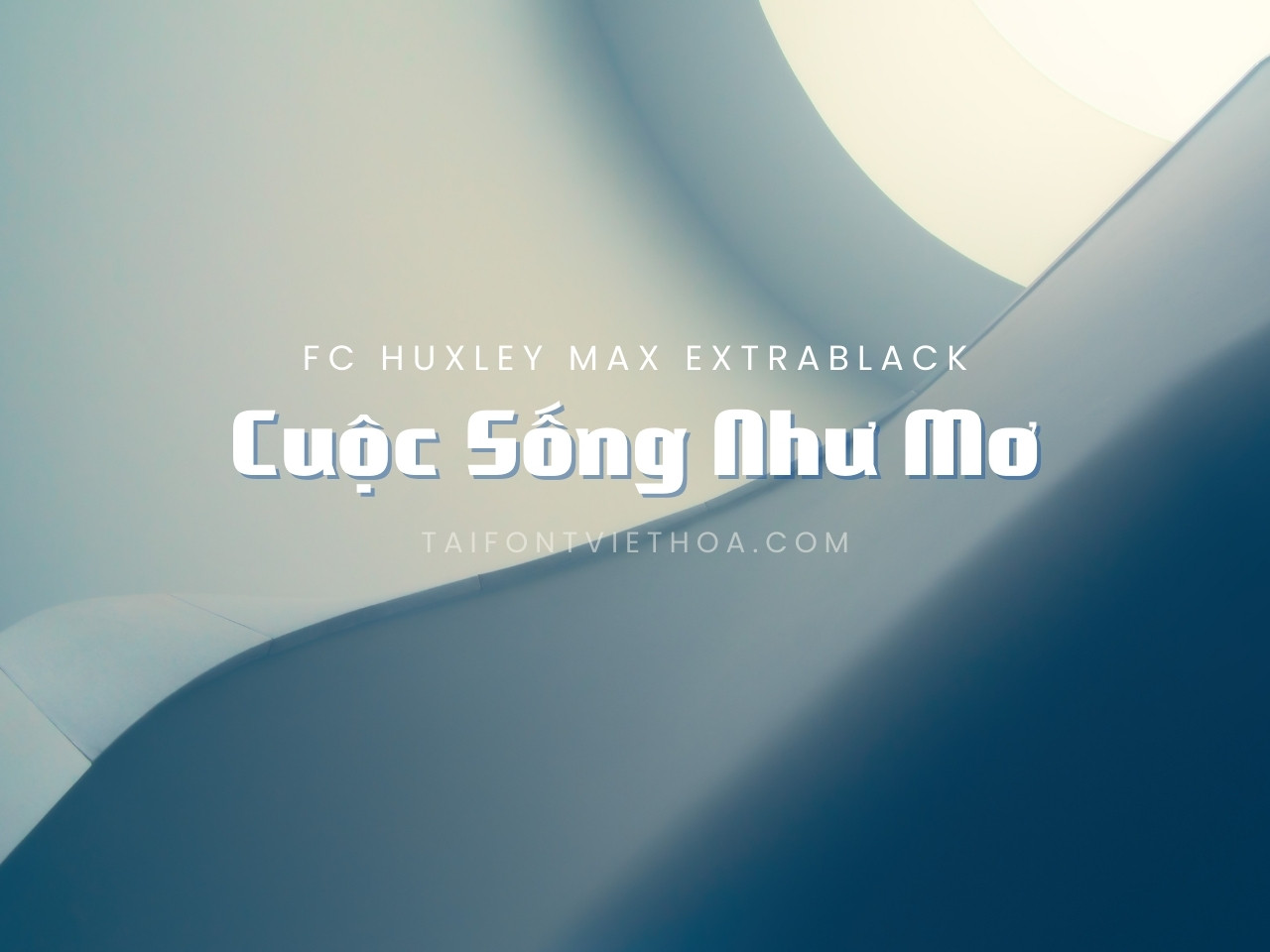
Giới thiệu về font Huxley Max và phiên bản Việt hóa
FC Huxley Max Extrablack là phiên bản Việt hóa từ bộ font “Huxley Max” – một thiết kế sans-serif mang phong cách hiện đại và đầy trọng lượng. Được phát triển bởi hãng thiết kế nổi tiếng Canada Type, font Huxley Max là bản mở rộng của kiểu chữ Huxley Vertical ra mắt từ những năm 1930, nhưng được tái thiết kế lại để phù hợp với hơi thở đương đại. Phiên bản Extrablack là biến thể nặng nhất, tạo ấn tượng mạnh trong các ứng dụng cần sự nổi bật và quyết đoán. Font hỗ trợ hơn 70 ngôn ngữ quốc tế sử dụng bảng chữ cái Latin mở rộng.
Bản Việt hóa được thực hiện bởi cộng đồng Font Chuẩn, giúp mở rộng khả năng sử dụng cho người dùng tại Việt Nam. Hệ thống dấu tiếng Việt được tích hợp trọn vẹn, đảm bảo tính thẩm mỹ và tương thích cao trong các dự án thiết kế. Font này được taifontviethoa.com tuyển chọn và hiệu chỉnh lại để đáp ứng nhu cầu thiết kế chuyên nghiệp, đặc biệt phù hợp với các dự án yêu cầu độ đậm cao, hiệu ứng thị giác mạnh và thông điệp dứt khoát.
Đặc điểm thiết kế nổi bật và các ứng dụng thực tiễn
FC Huxley Max Extrablack là kiểu sans-serif dạng geometric với đặc trưng là các nét thẳng, đều và dày – tạo ra hiệu ứng thị giác mạnh mẽ và sắc sảo. Các chữ cái có hình khối rõ ràng, phù hợp cho việc tạo tiêu đề, banner, poster quảng cáo hoặc các nội dung cần gây chú ý nhanh. Kiểu chữ này không có chân (sans-serif), nên giữ được sự tối giản và hiện đại trong tổng thể thiết kế.
Font rất phù hợp với các ngành nghề như công nghệ, thể thao, truyền thông, giải trí, thiết kế bảng hiệu và thương hiệu startup. Đặc biệt, nó mang lại hiệu quả cao khi sử dụng cho tiêu đề lớn trong các chiến dịch quảng cáo, typography poster hoặc các giao diện người dùng mang tính sáng tạo cao.